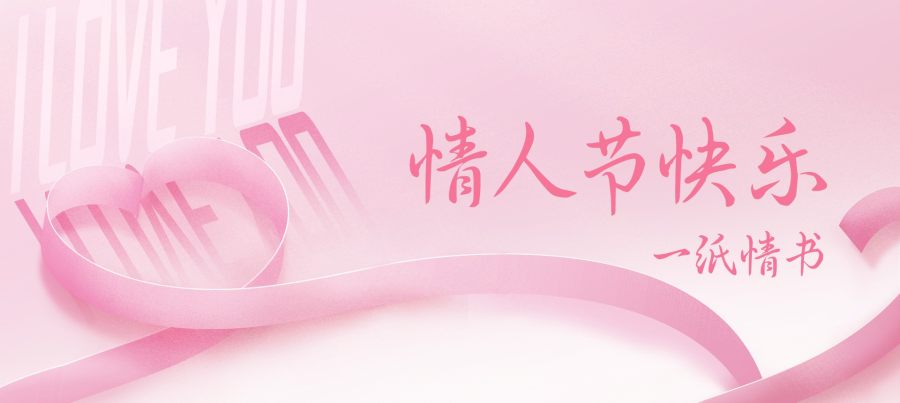
以前的我们,向喜欢的人表白,会翻遍自己的摘录本,找出最恰当的那句话,一笔一划写在漂亮的纸上,或托熟悉的人,或放进邮筒,等待那个人的回信...
现在还有人手写情书吗?
我想,能回答“有”的人,大概很少了。
现在,你是否也想你的ta在收到手写情书时,欢呼雀跃。
那你可以选择这款比较应时应景的一纸情书体,写下你对ta满满的情话。
一纸情书字体是由义启字库出品,该字体线条流畅顺滑,整体庄重,结实,字体浑厚有力十分耐看,棱角柔滑,装饰角的圆滑处理,使整款字体看起来既不缺少正式感又能增添个性。